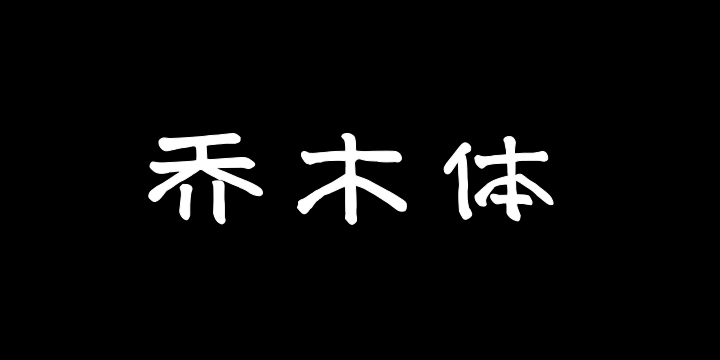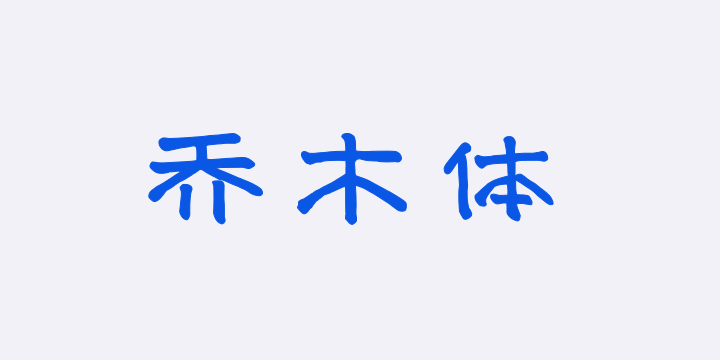
上首乔木体 By 上首造字 商用字体
字体全名: 上首乔木体
铸字厂: 上首造字
设计师: 胡博剑
字体简介: 上首乔木体,简体中文约6763字,字体线条粗细匀称,运笔自如,古朴中显现灵动,字韵变化多奇,生动活泼,体现文字所特有的艺术魅力。适用于搭配标志、广告标语、商业广告等高端属性。
所属分类: 手写体